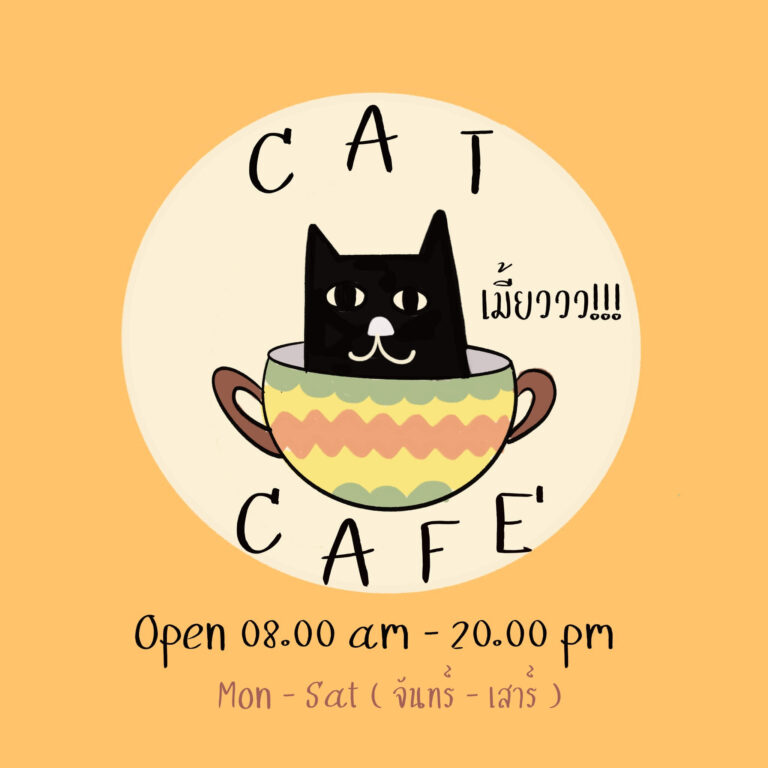
ฟอนต์ลายมือ สบายสบาย ใช้แล้วสบายตา สบายใจ แจกฟรีสำหรับใช้ส่วนตัว และไม่ได้นำไปใช้เชิงพาณิชย์ค่ะ
ที่มาของฟอนต์คือเราอยากทำฟอนต์ลายมือตัวเอง เอามาร่วมแบ่งปันกันค่ะ
อาจจะนำไปใช้ในงานเขียนไดอารี่ หรือเขียนสรุป หรือจะนำไปใช้ตกแต่งในงานต่างๆ ก็ได้เลยค่ะ ☺️
สบายสบาย (sabaisabai)